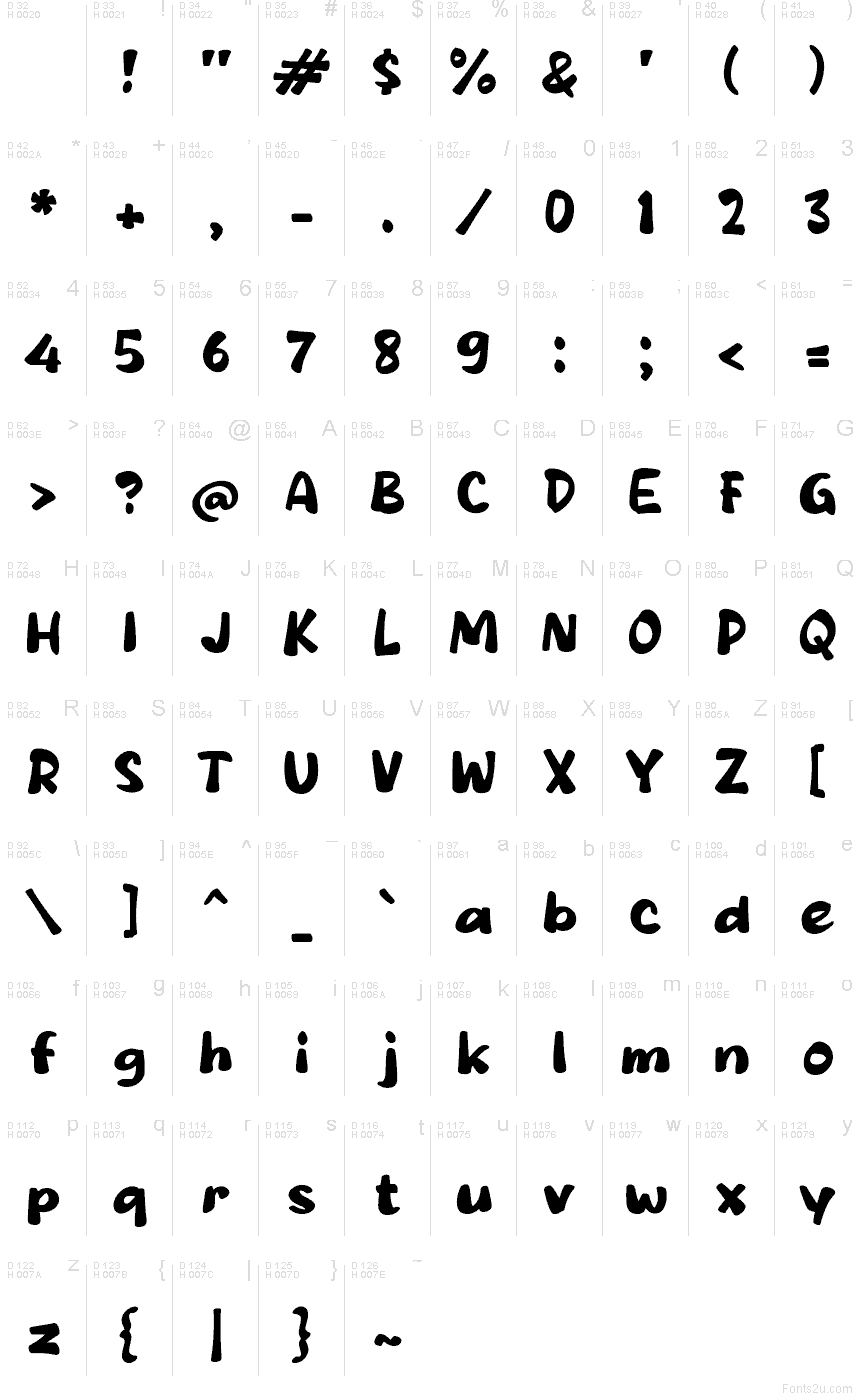
SABLONE
Sablone da Wep é uma fonte display gratuita no estilo cartoon, definida por uma silhueta inchada e elástica que faz com que cada letra pareça comprimida e ligeiramente desequilibrada. Essa massa densa, combinada com curvas irregulares e bordas tortas, confere ao lettering um balanço cômico e descontraído, em vez do acabamento polido de uma pintura manual.
Seu volume arredondado funciona muito bem em convites de festas infantis, embalagens de snacks, títulos estilo quadrinhos, cartazes escolares e miniaturas divertidas para YouTube. Ela se destaca em títulos curtos, onde sua forma macia e orgânica transforma algumas palavras em um elemento gráfico amigável em vez de apenas um texto comum.